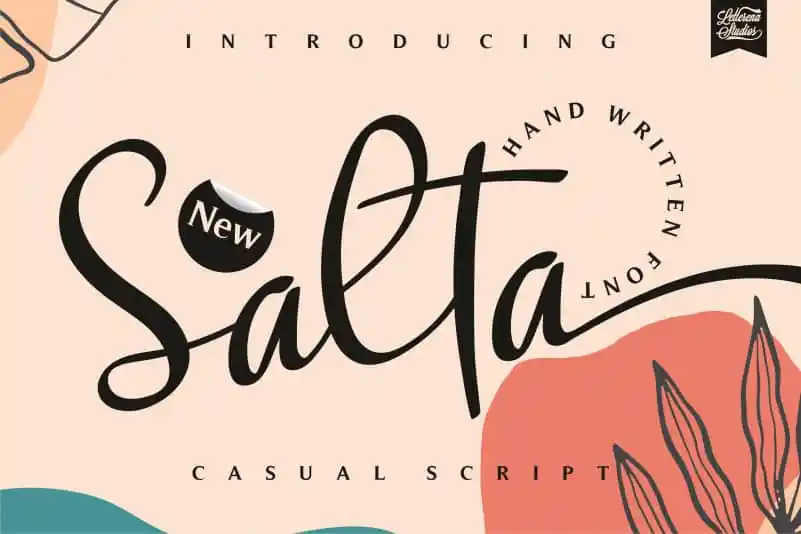
Salta Script Font – Download Grátis
A Salta Script Font é uma fonte escrita a mão que traz elegância e conforto ao seu projeto. Essencialmente ideal para criar logos, embalagens de produtos, cartões de convite e muitos outros elementos visuais que exijam um toque sofisticado e autêntico. Seu design gracioso é perfeito para a criação de uma variedade de projetos, como etiquetas, cartazes, estampas em mugs ou até mesmo fotos personalizadas. Esta fonte de escrita a mão é também uma excelente escolha para aqueles que buscam um charme próprio nas suas criações. Suas linhas elegantes e seus traços suaves proporcionam um toque único aos seus projetos, transformando-os em verdadeiros trabalhos de arte. O Salta Script Font é uma opção perfeita tanto para estilos tradicionais quanto para os mais modernos, tornando-a uma fonte versátil que pode ser usada em inúmeros campos e projetos. Sem dúvida, ela será a escolha certa para qualquer projeto que seja capaz de beneficiar-se do charme da escrita a mão.